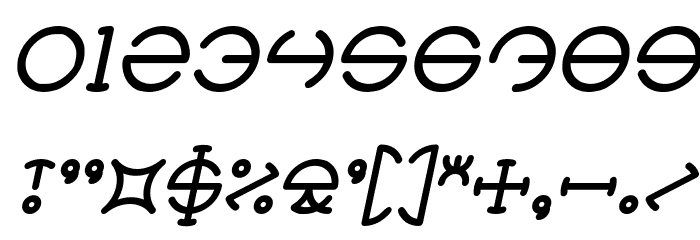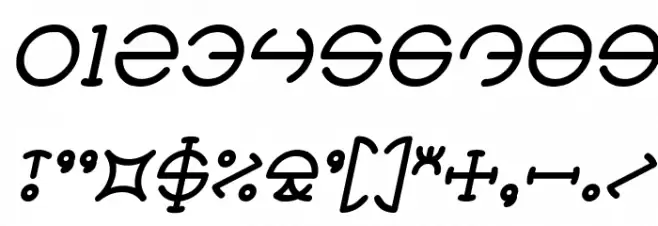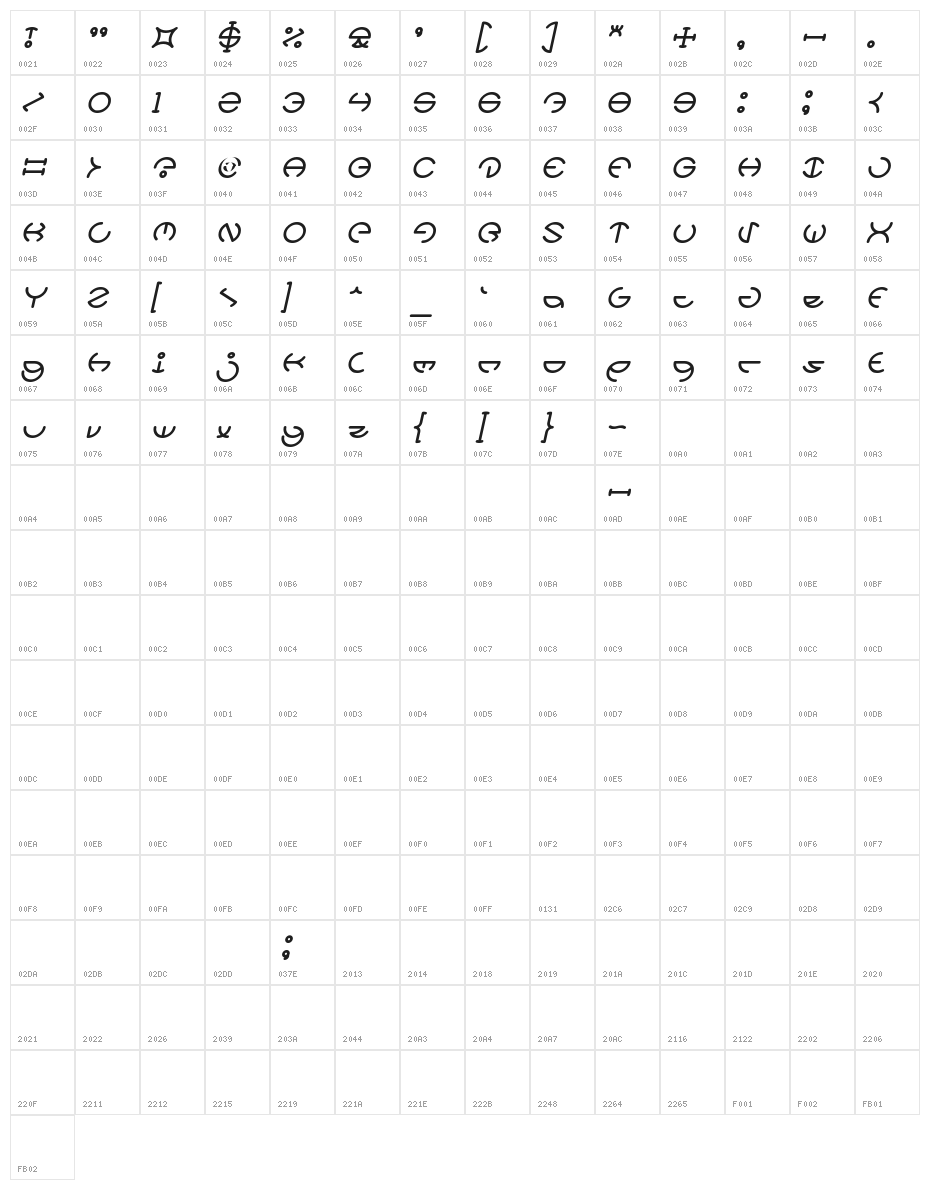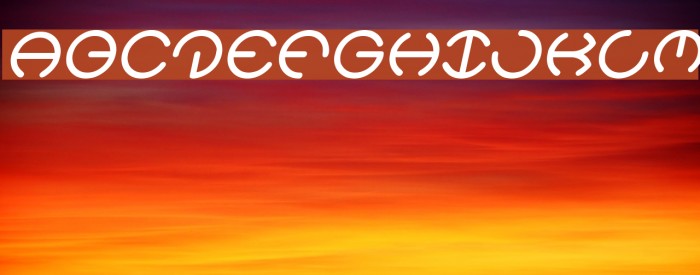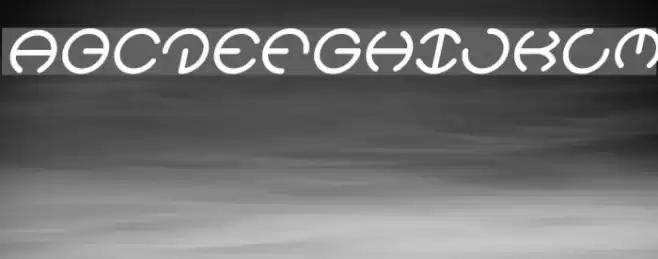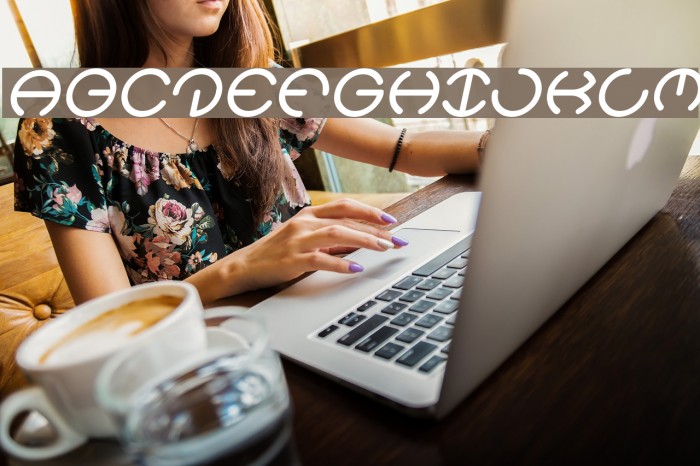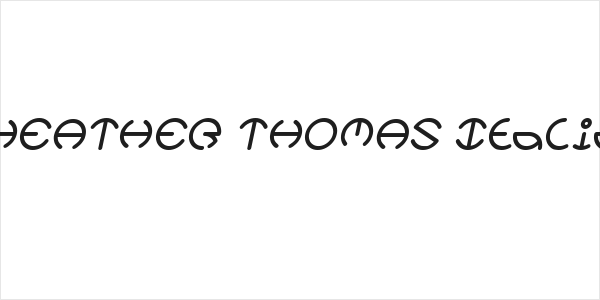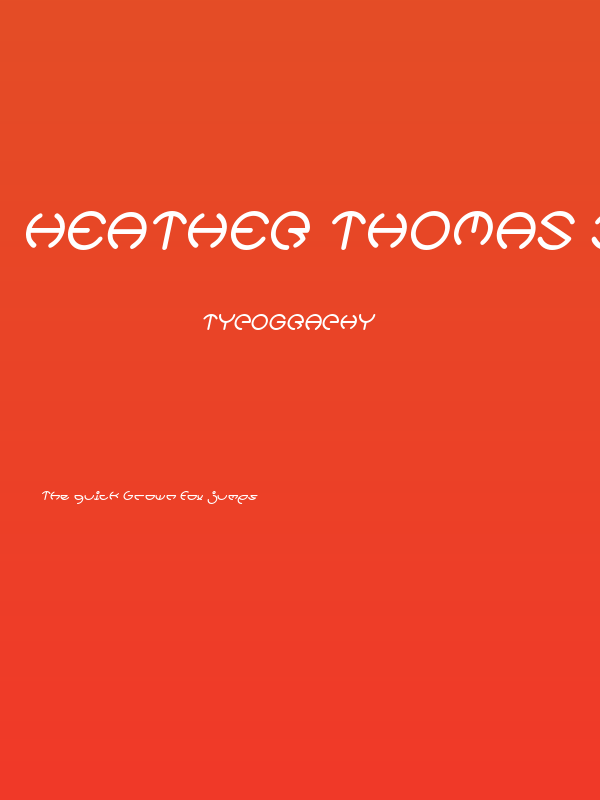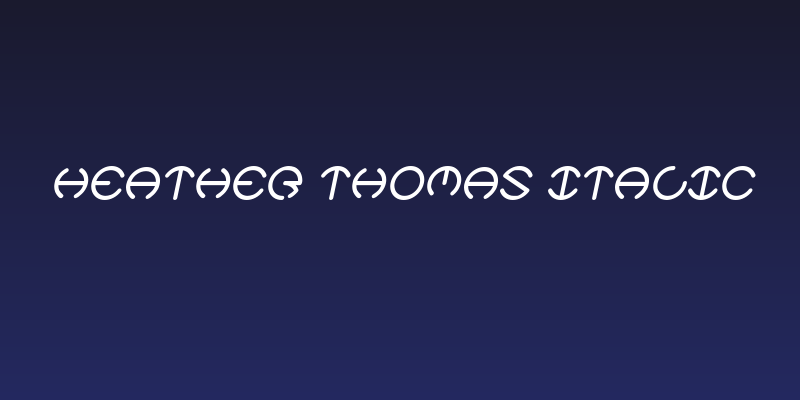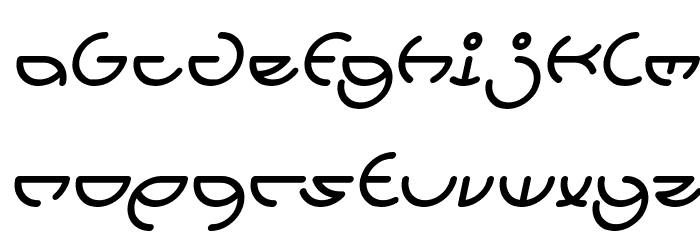
HEATHER THOMAS Italic Font
| 全体的なスタイル | Modern, Decorative |
| 用途 | Headlines, Logos, Creative projects |
| おすすめプロジェクト | Ideal for creative projects such as children's books, playful branding, or futuristic-themed designs. |